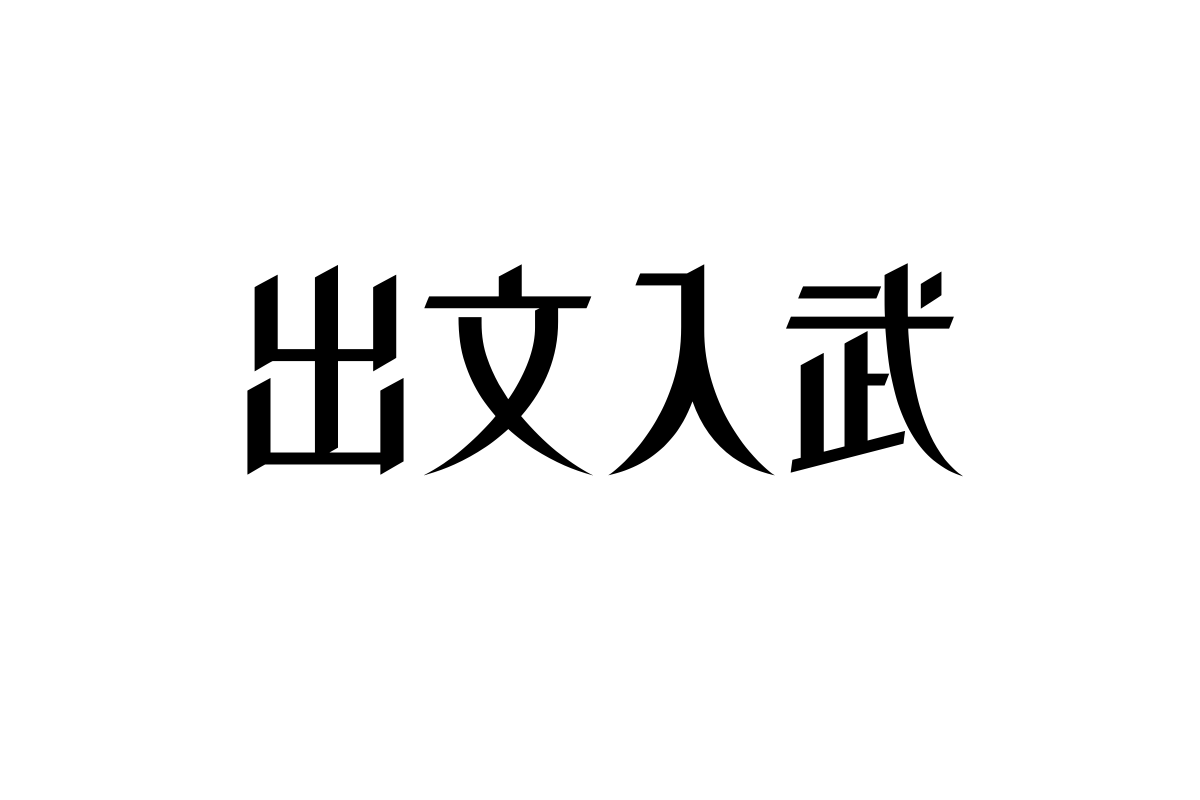
雅倩体是一种书法字体,以其优美的线条和独特的结构而闻名。这种字体的特点是笔画流畅,线条优美,给人一种优雅、高贵的感觉。它的结构严谨,每个字的笔画都有严格的规范,使得整个字体看起来非常整齐和和谐。
雅倩体的笔画粗细不一,有的笔画较粗,有的笔画较细,这使得整个字体看起来既有力度又有柔美。同时,这种字体的线条也有一定的弯曲度,使得整个字体看起来更加生动和富有变化。
总的来说,雅倩体是一种非常独特和美丽的字体,它的每一个笔画都充满了艺术感,让人看了就有一种深深的美感。